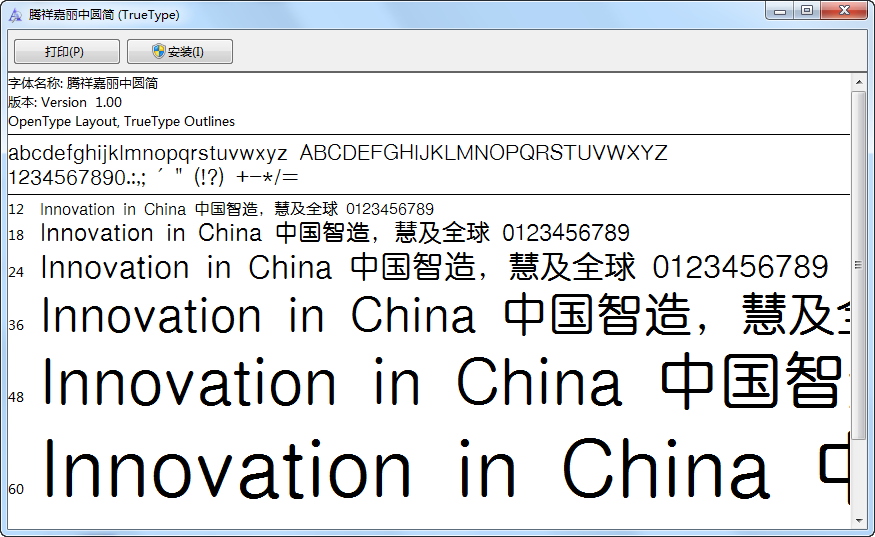
騰祥嘉麗中圓簡(jiǎn)是騰祥嘉麗圓體系列字庫(kù)的中圓字體。其中每個(gè)漢字都經(jīng)過(guò)精心設(shè)計(jì),筆畫(huà)柔美光潔、粗細(xì)均勻、結(jié)構(gòu)美觀。每個(gè)字的圓角、圓頭、勾形都極光潔、風(fēng)格統(tǒng)一 字形放大不變形,縮小顯示清晰,整款字庫(kù)有不同的顯示和打印效果,筆型嚴(yán)謹(jǐn)規(guī) 范,適用于正文排版。